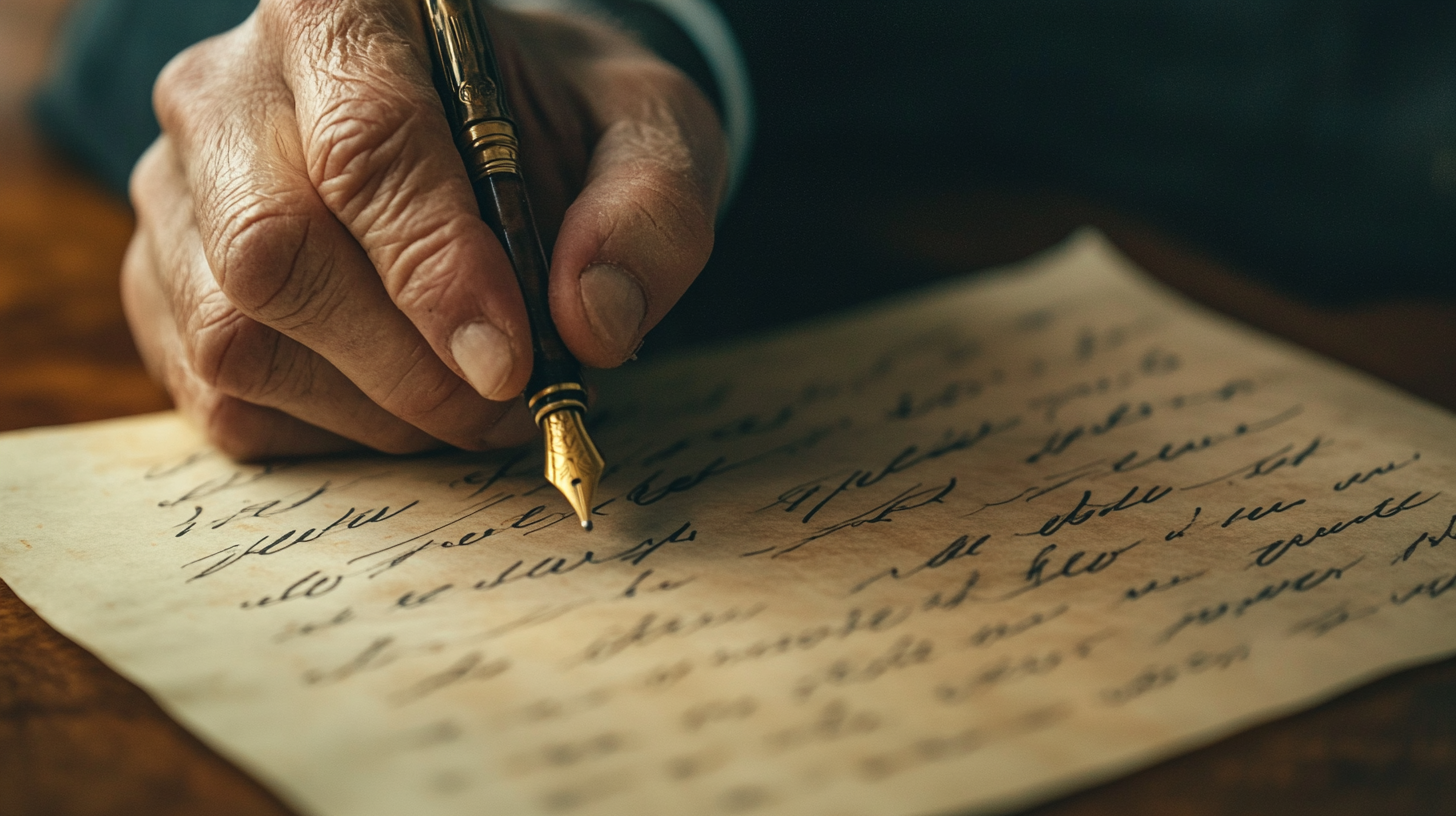
사람의 첫인상은 말투, 옷차림, 표정뿐만 아니라 글씨체에서도 강한 인상을 받을 수 있어요. 특히 손글씨는 그 사람의 성격과 꼼꼼함을 반영하기 때문에 좋은 첫인상을 남기는 데 중요한 요소가 될 수 있어요! ✍
만약 내 글씨가 너무 삐뚤빼뚤하거나 정돈되지 않았다면 글씨 교정을 통해 더욱 깔끔하고 세련된 이미지를 만들 수 있어요. 오늘은 글씨체가 첫인상에 미치는 영향과 더 나은 인상을 위해 교정할 수 있는 방법들을 알아볼게요! 😊
👀 글씨체와 첫인상의 관계
첫인상을 결정하는 요소는 다양하지만, 손글씨도 그중 하나라는 사실을 알고 계셨나요? ✍ 특히 메모나 서류를 직접 작성할 때, 상대방은 글씨체를 통해 나의 성격과 태도를 유추할 수 있어요. 😊
예를 들어, 깔끔하고 정돈된 글씨는 신뢰감과 성실함을 느끼게 해주고, 반대로 너무 급하게 쓰거나 삐뚤어진 글씨는 대충 쓴 듯한 느낌을 줄 수 있어요. 즉, 손글씨도 나의 이미지를 형성하는 중요한 요소랍니다! 💡
📊 글씨체별 첫인상 분석
글씨체 특징 주로 받는 인상 반듯한 정자체 획이 일정하고 글씨 크기가 균형 잡힘 신뢰감, 성실함 둥글고 부드러운 글씨 곡선이 많고 따뜻한 느낌 친근함, 다정함 날카롭고 각진 글씨 획이 강하고 직선적 결단력, 강한 성격 삐뚤빼뚤한 글씨 글씨 크기가 일정하지 않음 산만함, 급한 성격 이처럼 글씨체는 상대방에게 무의식적으로 나의 성격과 태도를 전달하는 중요한 역할을 해요! 그렇다면 첫인상을 좋게 만드는 글씨체는 어떤 특징을 가질까요? 🤔
✨ 첫인상을 좋게 만드는 글씨체 특징
글씨체도 말투나 옷차림처럼 첫인상을 좌우하는 중요한 요소 중 하나예요. 그렇다면 좋은 인상을 남기려면 어떤 글씨체를 가져야 할까요? 🤔
깔끔하고 정돈된 글씨는 신뢰감을 주고, 읽기 쉬운 글씨는 상대방에게 좋은 인상을 남겨줘요. 반면, 너무 날카롭거나 삐뚤어진 글씨는 부주의하거나 급한 인상을 줄 수 있어요! ✍
🌟 좋은 인상을 주는 글씨체의 특징
특징 설명 첫인상 효과 적당한 크기 너무 크거나 작지 않고 적절한 글씨 크기 유지 균형 잡힌 성격으로 보임 획이 일정한 글씨 획의 두께와 간격이 일정함 신뢰감과 성실한 이미지 부드러운 곡선 각지지 않고 자연스러운 곡선이 많음 온화하고 친근한 인상 적절한 자간과 행간 글자 간격과 줄 간격이 일정함 체계적이고 정리된 느낌 이처럼 글씨를 조금만 정돈해도 상대방이 나를 더 신뢰하고 긍정적으로 바라볼 수 있어요! 😊 그렇다면 손글씨로 성격을 표현하는 방법도 있을까요? 다음 섹션에서 함께 알아볼게요! ✨
🖊 손글씨를 통한 성격 표현
글씨체는 단순히 글을 쓰는 도구가 아니라 자신의 성격과 감성을 표현하는 방법이 될 수도 있어요. ✍ 사람마다 필체가 다른 이유는 손의 습관뿐만 아니라 내면의 성향과 감정이 글씨에 자연스럽게 반영되기 때문이에요. 😊
예를 들어, 정갈하고 반듯한 글씨를 쓰는 사람은 신중하고 꼼꼼한 성격일 가능성이 높고, 둥글고 부드러운 글씨를 쓰는 사람은 온화하고 다정한 성격일 가능성이 높아요. 그렇다면, 글씨체별 성격 특징을 살펴볼까요? 🤔
📌 글씨체로 보는 성격 유형
글씨체 유형 특징 성격 분석 작고 정돈된 글씨 획이 일정하고 세밀함 신중하고 꼼꼼한 성격 둥글고 부드러운 글씨 곡선이 많고 유연함 온화하고 친절한 성격 크고 시원한 글씨 글자가 큼직하고 공간이 넉넉함 외향적이고 자신감 넘침 날카롭고 각진 글씨 획이 강하고 직선적 논리적이고 결단력 있는 성격 물론 글씨체만으로 성격을 단정할 수는 없지만, 손글씨를 통해 그 사람의 성향을 어느 정도 유추해볼 수 있어요! ✨ 그렇다면 비즈니스 환경에서는 어떤 글씨체가 좋을까요? 다음 섹션에서 함께 알아볼게요! 💼
💼 비즈니스에서 중요한 글씨체
직장이나 비즈니스 환경에서는 글씨체가 더욱 중요한 역할을 해요! ✍ 계약서 서명, 회의록 작성, 고객 응대 메모 등 많은 상황에서 손글씨가 사용되기 때문이죠. 😊
특히 비즈니스 글씨체는 가독성이 좋고 신뢰감을 주는 스타일이 중요해요. 너무 개성이 강하거나 흐트러진 글씨는 프로페셔널한 이미지를 떨어뜨릴 수 있어요! 🤔
📊 신뢰감을 주는 비즈니스 글씨체
글씨체 특징 설명 비즈니스 효과 반듯한 정자체 획이 일정하고 글씨 크기가 균형 잡힘 신뢰감과 전문성 강조 적절한 글자 간격 글자 간격이 너무 좁거나 넓지 않음 읽기 쉽고 체계적인 인상 깔끔한 필기체 필기 속도를 유지하면서도 가독성이 높음 메모 및 기록 시 신뢰감 상승 획이 너무 강하지 않은 글씨 획이 너무 굵거나 날카롭지 않음 부드럽고 친근한 인상 비즈니스 환경에서는 깔끔하고 정돈된 글씨가 더욱 신뢰감을 줘요. 😊 그렇다면, 이런 글씨체를 만들기 위해 어떤 연습 방법이 효과적일까요? 다음 섹션에서 알아볼게요! ✨
📝 깔끔한 글씨를 위한 실전 연습법
깔끔하고 정돈된 글씨를 쓰려면 단순히 많이 쓰는 것보다 올바른 연습법을 따르는 것이 중요해요. ✍ 기본적인 획 연습부터 자간, 행간 조절까지 체계적인 연습이 필요하답니다! 😊
오늘은 글씨체를 빠르고 효과적으로 교정할 수 있는 실전 연습법을 소개해드릴게요! 이 연습법을 따라 하면 누구나 보기 좋은 글씨체를 만들 수 있어요. ✨
📖 글씨 교정 실전 연습법
연습법 설명 효과 기본 획 연습 직선, 곡선, 대각선 등을 반복 연습 획이 일정해지고 필기 감각 향상 모눈 종이에 쓰기 글자의 크기와 간격을 맞추며 연습 균형 잡힌 글씨체 형성 속도 조절 연습 처음엔 천천히, 점점 속도를 올리며 필기 획이 깔끔하고 안정적으로 변함 필사 연습 책이나 명언을 따라 쓰며 글씨체 익히기 자연스럽고 부드러운 필기체 완성 위 연습법을 꾸준히 실천하면 글씨가 점점 정돈되고, 가독성이 향상될 거예요. 😊 그렇다면 글씨를 교정하면 자신감도 올라갈까요? 다음 섹션에서 함께 알아볼게요! ✨
💪 악필을 교정하면 자신감도 올라간다!
악필 때문에 손글씨를 보여주기 꺼려진 적 있으신가요? 😢 하지만 글씨체가 변하면 나에 대한 인식도 바뀌고, 자신감까지 올라갈 수 있어요! ✨
글씨는 단순한 도구가 아니라 나의 성격과 태도를 반영하는 중요한 요소예요. 정돈된 글씨를 쓰면 상대방에게 더 좋은 인상을 줄 수 있고, 스스로도 더 당당한 마음을 가질 수 있답니다. 😊
🚀 글씨 교정 후 달라지는 점
변화 설명 긍정적인 효과 자기 만족감 상승 더 정돈된 글씨를 보면 뿌듯함을 느낌 자존감 & 자신감 향상 첫인상 개선 깔끔한 글씨는 신뢰감을 줌 대인관계에서 긍정적인 영향 업무 능력 향상 빠르고 정돈된 필기가 가능해짐 효율적인 업무 처리 필기 습관 개선 올바른 필기 자세와 속도를 조절함 손 피로 감소 & 집중력 향상 악필 교정은 단순히 예쁜 글씨를 만드는 것이 아니라 자신감과 삶의 질을 높이는 좋은 습관이에요. ✨ 이제 글씨 교정에 대해 궁금한 점을 FAQ에서 확인해볼까요? 🤔
Q1. 글씨 교정을 하면 정말 첫인상이 좋아질까요?
A1. 네! ✍ 깔끔하고 정돈된 글씨는 성실하고 신뢰감 있는 인상을 줄 수 있어요. 특히 직장이나 학교에서 메모나 서류를 작성할 때 더 좋은 평가를 받을 가능성이 높아요. 😊
Q2. 악필을 교정하는 데 얼마나 걸릴까요?
A2. 하루 15~30분씩 꾸준히 연습하면 보통 2~4주 안에 눈에 띄는 변화를 볼 수 있어요. 완전히 습관화하려면 최소 2~3개월 정도 꾸준한 연습이 필요해요. 💪
Q3. 글씨 교정에 가장 효과적인 연습 방법은 무엇인가요?
A3. 기본 선 연습 → 모눈 노트 활용 → 필사 연습을 조합하면 효과적이에요. 특히 모눈 종이에 글씨 크기와 간격을 맞춰 쓰는 연습이 큰 도움이 돼요! 📝
Q4. 필체가 성격과도 관련이 있나요?
A4. 네, 어느 정도 관련이 있어요! 예를 들어 반듯한 글씨를 쓰는 사람은 꼼꼼하고 신중한 성격일 가능성이 높고, 둥글고 부드러운 글씨를 쓰는 사람은 친근하고 온화한 성격일 확률이 커요. 😊
Q5. 비즈니스 환경에서 좋은 글씨체는 어떤 스타일인가요?
A5. 가독성이 높고 정돈된 글씨체가 좋아요! 획이 일정하고 글자 간격이 균일한 글씨는 신뢰감을 주고, 프로페셔널한 이미지를 만들 수 있어요. 💼
Q6. 글씨 교정을 위해 어떤 필기구를 사용하는 게 좋을까요?
A6. 초보자는 2B 연필이나 유성 볼펜을 추천해요. 손가락 위치를 잡아주는 그립 연필을 사용하면 올바른 필기 자세를 유지하는 데 큰 도움이 돼요! ✏
Q7. 글씨를 쓸 때 손에 힘이 너무 많이 들어가는 경우 어떻게 해야 하나요?
A7. 손을 가볍게 쥐고, 필기 전 손 스트레칭을 해보세요! 손악력기나 실리콘 핸드 그립볼을 활용하면 필기할 때 힘을 조절하는 연습을 할 수 있어요. ✋
Q8. 꾸준히 연습해도 글씨가 잘 안 변하는 경우 어떻게 해야 하나요?
A8. 너무 빨리 변화를 기대하지 마세요! 😊 잘못된 습관이 오래 지속되었다면 교정하는 데 시간이 걸릴 수 있어요. 모눈 노트를 활용해 기본적인 선 연습부터 차근차근 시작해보세요! 🚀
이제 글씨 교정을 통해 첫인상을 바꿀 준비가 되셨나요? ✨ 오늘부터 꾸준히 연습해서 나만의 예쁜 글씨체를 만들어보세요! 😊